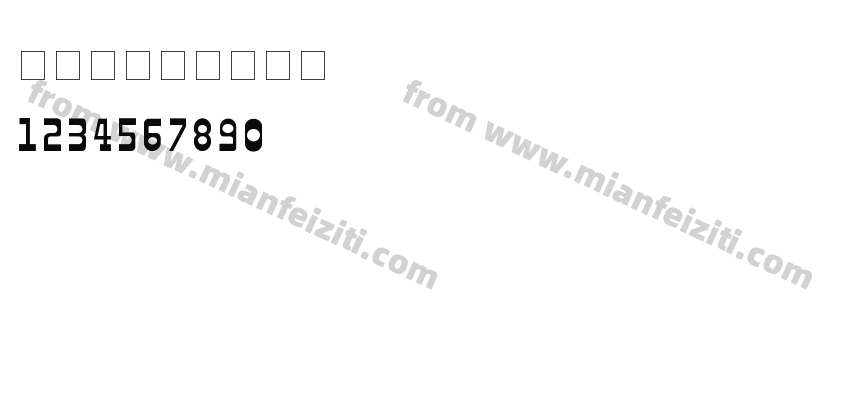
增值税专用发票号码字体是专为增值税发票而开发的一款字体,全称又叫做增值税专用发票号码字体,该字体线条粗细适中,字形端正大方得体,整体非常出色,可以应用于文本装潢、信息展示、网页设计、篆刻制模、数据制作、装潢设计、计算艺术设计、视觉设计、字帖等一切合法应用场景
本款“增值税专用发票号码”是一款书写很新颖的字体,字体大方,适合各种设计作品使用!欢迎下载!